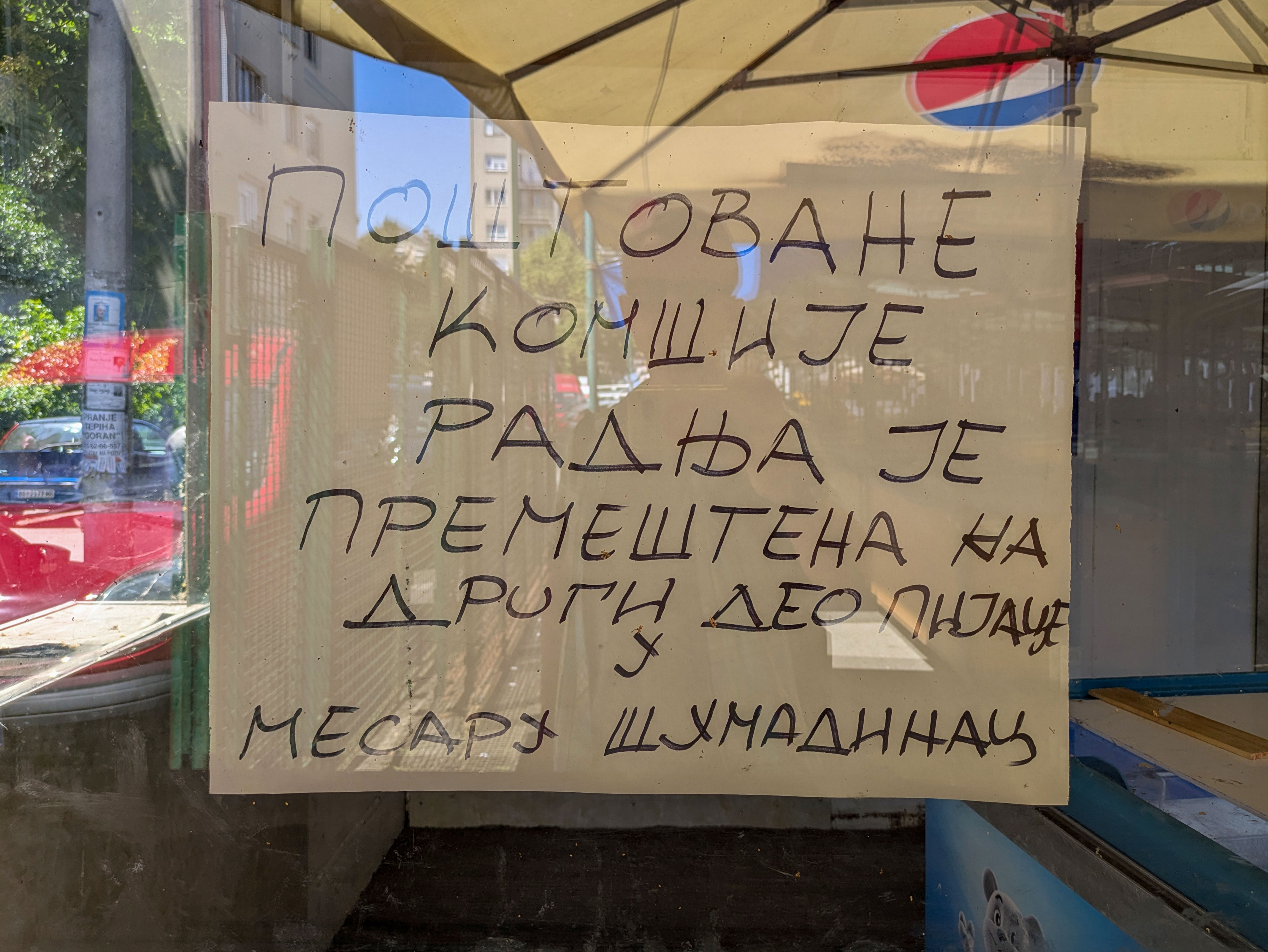
Radnja Je Premeštena
handwriting
Poštovane /
komšije /
radnja je /
premeštena na /
drugi deo pijace /
u /
mesaru Šumadinac
Dear /
neighbours /
the shop /
has been moved to /
another part of the market /
into the Šumadinac butcher's